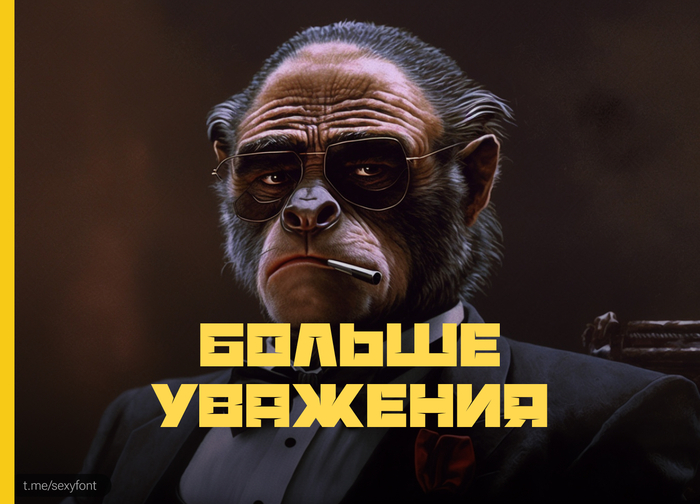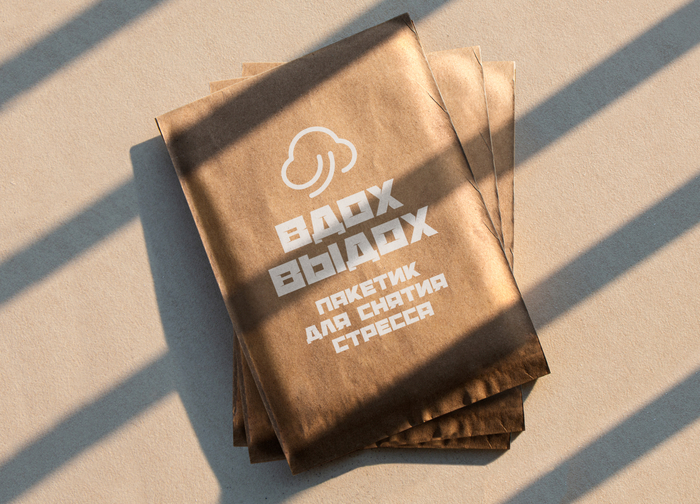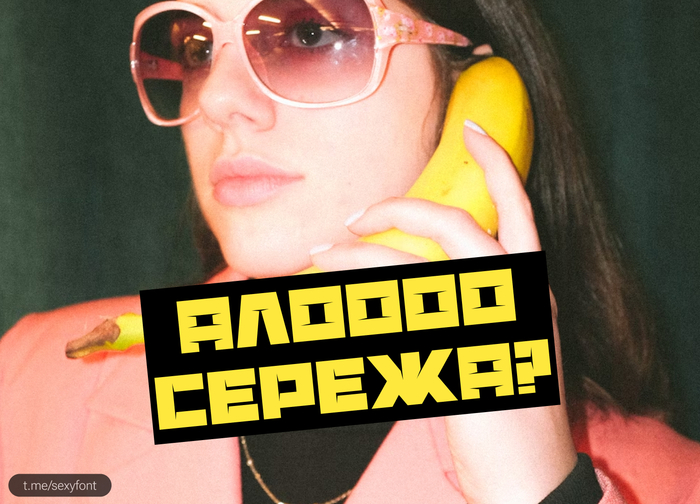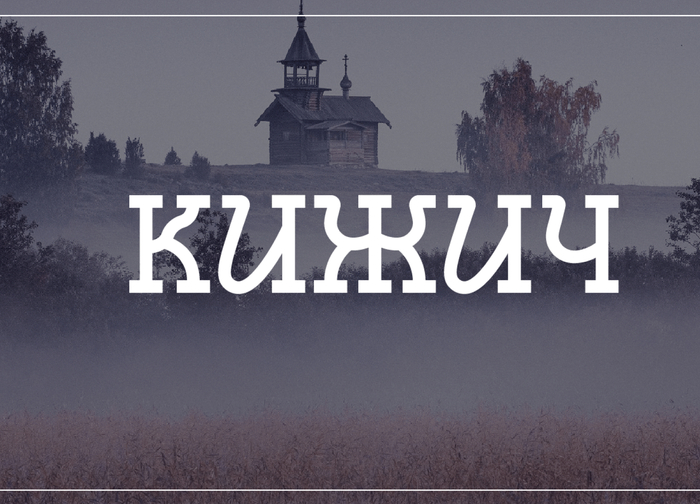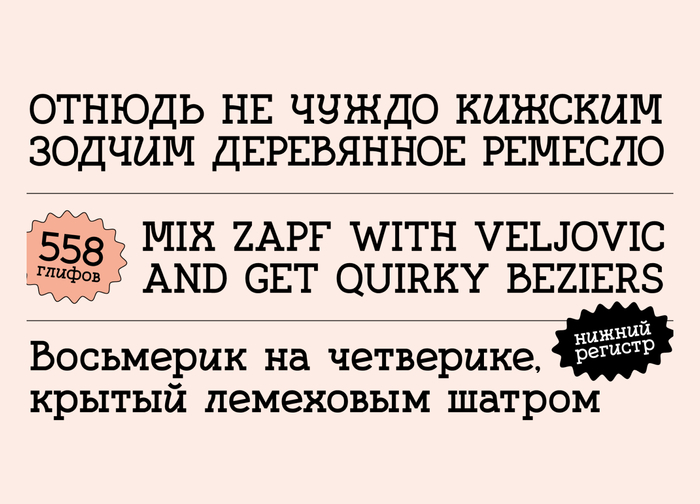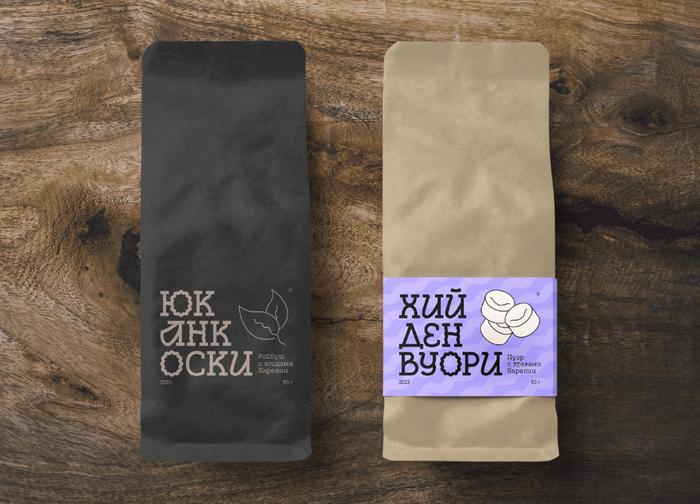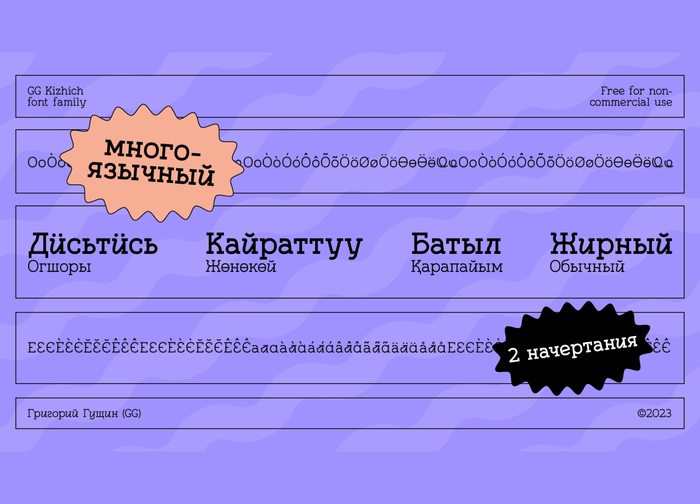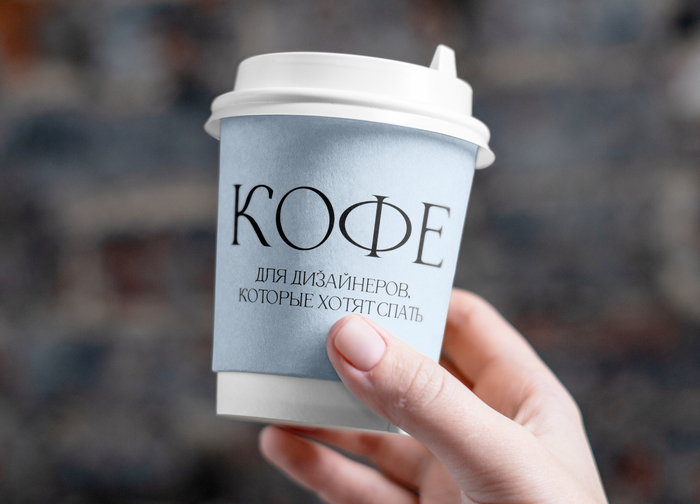
Кириллические шрифты
Шрифт ustroke rough
Веселый и почеркушный шрифт) Шрифт ustroke rough, нарисованный от руки, имеет неровный, колючий вид, что делает его уникальным даже среди других шрифтов, нарисованных от руки. Формат файла - TTF, содержит прописные буквы, цифры и поддерживает латинские и кириллические символы. Автор: Tikhon Reztcov. Бесплатно для всего.
Шрифт Нижегородский
Шрифт «нижегородский» Создан, как эксперимент по созданию современной версии древнерусской вязи. Похож на шрифт «доброзначный»от Панфилова) Кто в теме, тот поймет. Интересный акцидентный шрифтец. Хорошо читаемый и довольно универсальный в использовании. Бесплатно для всего. Автор: Alexander Shimanov
Шрифт Ганеша. Индийская стилистика
हाय! Намасте друзья! Ловите необычный шрифт в индийской стилистики. Говорят, что этот шрифт настолько похож на местный, что его понимают даже индусы. Редкая стилистика, не встречал такой. Бесплатно для личного и коммерческого использования. Автор: Ксения Карнаухова.
Шрифт киберпанк. Кириллица
Шрифт Киберпанк. Хайп почти прошел, а шрифт остался) Использовать максимум в 1 коротком слове. Иначе читаемость сразу теряется. Определенно только декоративные цели, а не информативные. Меня все равно обматерят за нечитаемость. Но опубликовать не имею права ) Автор кириллизации: FONTS BY LYAJKA
Цветочный шрифт
Флора. Очень красивый шрифт с узорами от цветов. Идеально для тематик красоты, здоровья, органики и т.п С лицензией все не очень понятно) Автор оригинала andrew pixel. Затем шрифт перевели на русский язык другие авторы. Не знаю насколько это было легально, скорее всего нет 😃 Но думаю как минимум для персонального использования (для себя) можно.
Банановый кирпич. Шрифт
Банановый кирпич. Яркий, пухлый, заметный банановый шрифтец. Отлично для баннеров и плакатов) Для лучшей читаемости использовать только в коротких предложениях. Ууууу. Автор: artmaker
Шрифт кижич. Кириллица
Необычный шрифт с заческами. Хорош впишется в темы путешествий, музеев, и другой исторической суеты) Шрифт имеет тонкое и жирное начертание. Бесплатно для персонального использования. Автор: Grigorij Gushchin
Красивый шрифт. Беролд. Кириллица
Роскошный шрифт с элегантными засечками. А название то такое. Berold. Что-то на бородато-бохатом. Отлично впишется в открытки, в постеры, в оформление сообществ. Бесплатно для личного использования. Судиться с вами сомневаюсь, кто будет) Автор с Индонезии. Автор: joko setiono. Презентация моя.